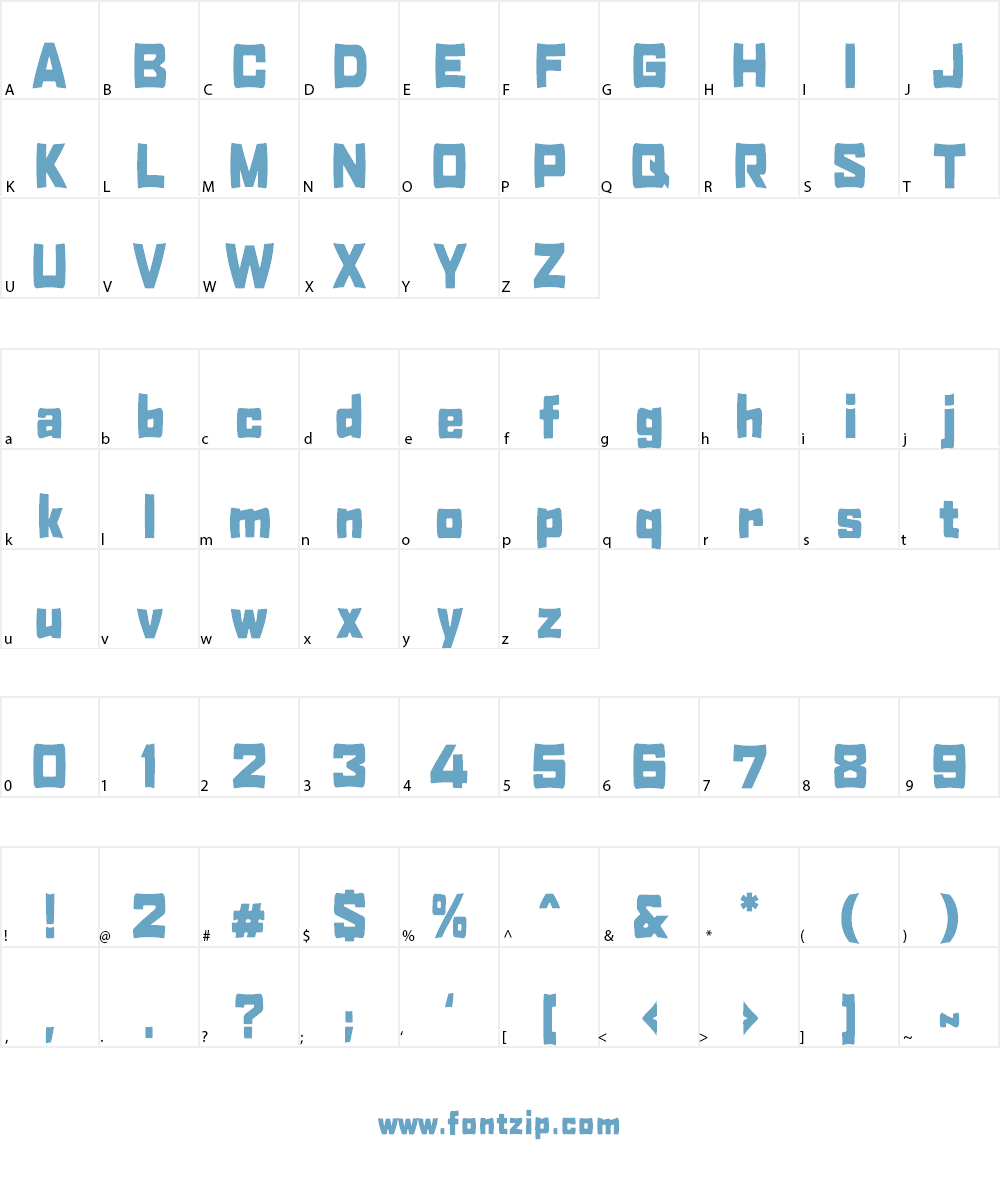
La forma de las letras está inspirada en la deformación de letras de goma, esas que estan formadas por capas de colores, cuando son presionadas con los dedos índice y pulgar, en su parte superior e inferior creando así una curva cóncava, y a su vez una curva convexa en los laterales de las letras.
Se trata de una fuente display, gruesa, sin serif y condensada, dispone de todos los caracteres latinos (369) y se puede usar para todos los idiomas europeos.
Con esta tipografía puedes componer posters, affiches y carteles publicitarios o usarla para diseñar tus folletos, flyers o publicaciones, ideal para títulos y grandes rótulos.